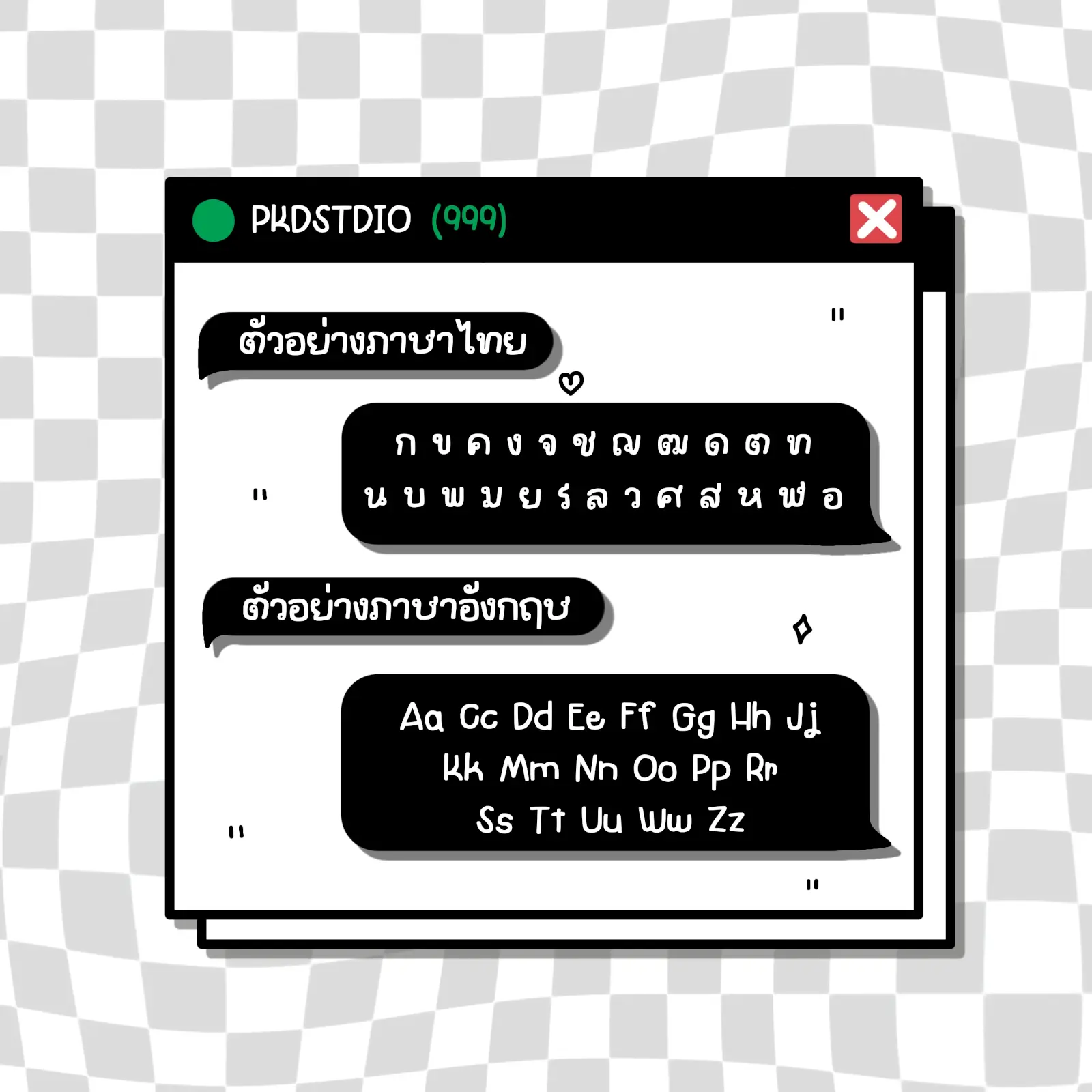
แพนดาร่าฟอนต์ (PKD PANDARA) – ฟอนต์ลายมือน่ารัก สดใส เป็นกันเอง เหมาะสำหรับงานคอนเทนต์ โพสต์โซเชียล สติกเกอร์ คาเฟ่ และงานออกแบบทั่วไป
- มีตัวอักษรโปร่งผสมในบางตำแหน่ง
- ไม่มีตัวอักษรโปร่งผสม
- รองรับภาษาไทย ภาษาอังกฤษ ตัวเลข และสัญลักษณ์
แพนดาร่า (PKD PANDARA)